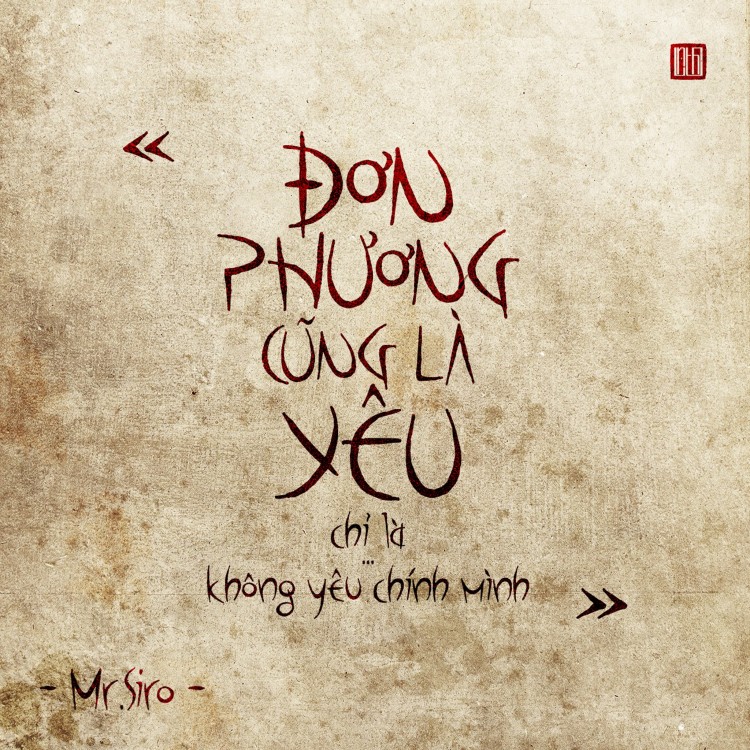
Tải Ngay Font việt hóa LNTH Poseidon AOE Miễn Phí Cho Thiết Kế Đồ Họa
Trong thế giới thiết kế đồ họa hiện đại, việc lựa chọn một bộ Font Chữ phù hợp đóng vai trò quyết định đến tính thẩm mỹ của sản phẩm. Một trong những cái tên đang thu hút sự chú ý của cộng đồng thiết kế chính là Font việt hóa LNTH Poseidon AOE. Đây là bộ phông chữ mang phong cách mạnh mẽ, uy nghi, lấy cảm hứng từ hình tượng vị thần biển cả Poseidon trong thần thoại Hy Lạp. Với các đường nét sắc sảo và hình khối vững chãi, bộ font này cực kỳ phù hợp cho các dự án yêu cầu sự chuyên nghiệp, cá tính và độc đáo tại Việt Nam hiện nay.
Đặc điểm nổi bật của Font việt hóa LNTH Poseidon AOE
Phong cách thiết kế và ứng dụng thực tế
Font việt hóa LNTH Poseidon AOE sở hữu những đường nét mang đậm chất sử thi, tạo cảm giác quyền lực và cổ điển nhưng không kém phần hiện đại. Điểm cộng lớn nhất của bộ font này chính là khả năng hiển thị tiếng Việt hoàn hảo, không bị lỗi dấu, giúp các bạn học sinh và giáo viên dễ dàng ứng dụng vào việc làm slide bài giảng, thiết kế bìa sách hay tạo các ấn phẩm truyền thông cho nhà trường. Ngoài ra, các nhà thiết kế còn ưu tiên sử dụng Poseidon AOE trong việc làm logo, poster phim hoặc các banner quảng cáo sự kiện thể thao nhờ vào độ dày của chữ và tính nhận diện rất cao.
Để tận dụng tối đa vẻ đẹp của Font việt hóa LNTH Poseidon AOE, người dùng nên kết hợp phông chữ này với các gam màu trầm như xanh biển sâu, vàng đồng hoặc trắng bạc. Việc cài đặt cũng rất đơn giản, bạn chỉ cần tải tệp định dạng .otf hoặc .ttf về máy tính, sau đó nhấn chuột phải và chọn Install. Sau khi cài đặt, font sẽ tự động xuất hiện trong các phần mềm phổ biến như Microsoft Word, PowerPoint hay Photoshop. Hãy nhớ căn chỉnh khoảng cách giữa các chữ cái (kerning) một cách hợp lý để nội dung luôn dễ đọc và chuyên nghiệp nhất.
Tổng kết về bộ font chữ độc đáo